So ändern Sie Instagram-Schriftarten für Ihr Profil und Ihre Bildunterschriften
Auf Instagram stehen zwar neun verschiedene Schriftarten für Ihre Storys zur Auswahl, doch für Ihre Profilinformationen, regulären Bildunterschriften und Kommentare müssen Sie sich mit einer einzigen, etwas eintönigen serifenlosen Schrift begnügen. Hier erfahren Sie, wie Sie diese Beschränkungen umgehen und Ihre Texte aufpeppen können.
Wie funktionieren individuelle Instagram-Schriftarten?
Instagram verwendet standardmäßig die Schriftart Proxima Nova für kleinere Textbereiche wie Kommentare und Bildunterschriften. Es gibt keine direkte Möglichkeit, diese Einstellung zu ändern, aber es gibt einen Trick, um dies zu umgehen.
Um verschiedene Alphabete, Satzzeichen, Schriftsysteme und Emojis zu unterstützen, nutzt Instagram einen Großteil des Unicode-Zeichensatzes. Dies beinhaltet mathematische Symbole (÷), griechische Buchstaben (Ω), die in der Wissenschaft verwendet werden, hebräische Buchstaben (א) und auch einige grundlegende Buchstabenstile wie 𝕿𝖊𝖝𝖙 𝖎𝖓 𝕬𝖓𝖛𝖊𝖗𝖘𝖊𝖗 𝕾𝖈𝖍𝖗𝖎𝖋𝖙, 𝙼𝚊𝚝𝚝𝚎𝚛 𝚠𝚒𝚝𝚑 𝙰 𝚂𝚎𝚛𝚒𝚏 𝙵𝚘𝚗𝚝, und ⓛⓔⓣⓣⓔⓡⓢ ⓘⓝ ⓒⓘⓡⓒⓛⓔⓢ. Durch die Kombination von verschiedenen Glyphen lassen sich sogar Schriftarten wie eine auf dem Kopf stehende Schrift (ʇuoɟ uʍop ǝpısdn uɐ) oder ฬђคՇєשєг ץ๏ย ςคɭɭ Շђเร erstellen.
Nachdem Sie nun die Grundlagen kennen, zeigen wir Ihnen, wie Sie diese alternativen Schriftarten ganz einfach auf Instagram verwenden können.
So fügen Sie ausgefallene Schriftarten zu Bildunterschriften und Bios hinzu
Während einige Unicode-Zeichen direkt über eine normale Tastatur eingegeben werden können, ist es einfacher, diese aus einer App zu kopieren und einzufügen, wenn Sie mehr als nur ein "t" durch ein +-Zeichen ersetzen möchten.
Besuchen Sie mit Ihrem Smartphone die Seite CoolFont.org und geben Sie dort Ihre Bildunterschrift oder Ihren Kommentar ein. Die Website bietet Ihnen etwa 100 verschiedene Textstile, von cool bis kaum lesbar. Nutzen Sie die Schaltfläche "Dekorieren", um zusätzliche Textverzierungen wie Herzen, Sterne und andere Muster hinzuzufügen.
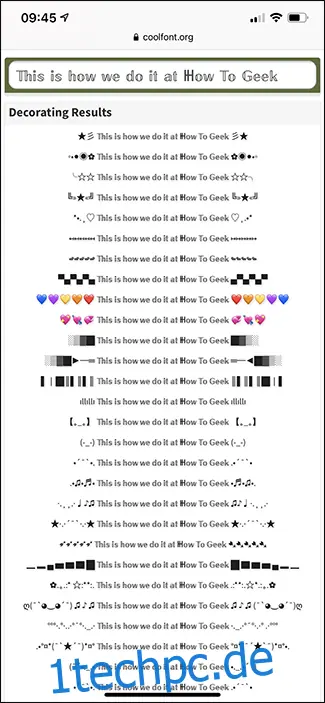
Wenn Sie mit dem Erscheinungsbild des Textes zufrieden sind, markieren Sie ihn und tippen Sie auf "Kopieren" oder klicken Sie einfach auf die Schaltfläche "Kopieren". Danach können Sie den Text in ein beliebiges Textfeld auf Instagram einfügen.
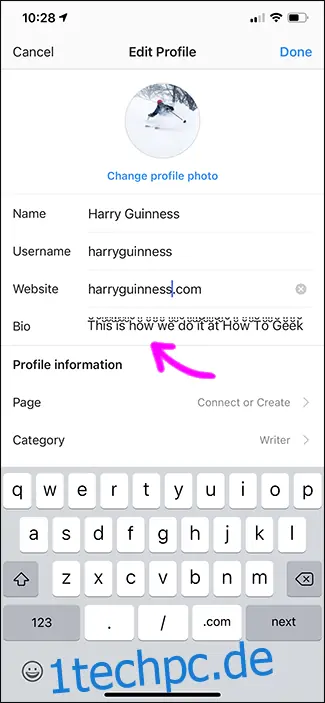
Diese Methode funktioniert auch in Instagram Stories, sieht dort aber wahrscheinlich nicht so gut aus wie die integrierten Optionen.
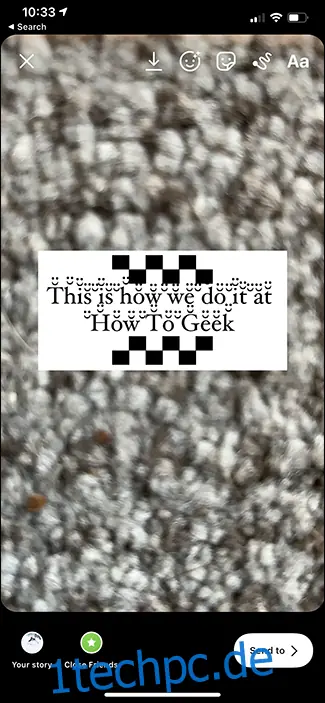
Dieselbe Technik kann genutzt werden, um Schriftarten auf anderen Social-Media-Plattformen, wie Twitter und Facebook, die Unicode unterstützen, zu ändern. Allerdings sollte man dabei immer darauf achten, dass die Texte gut lesbar bleiben.